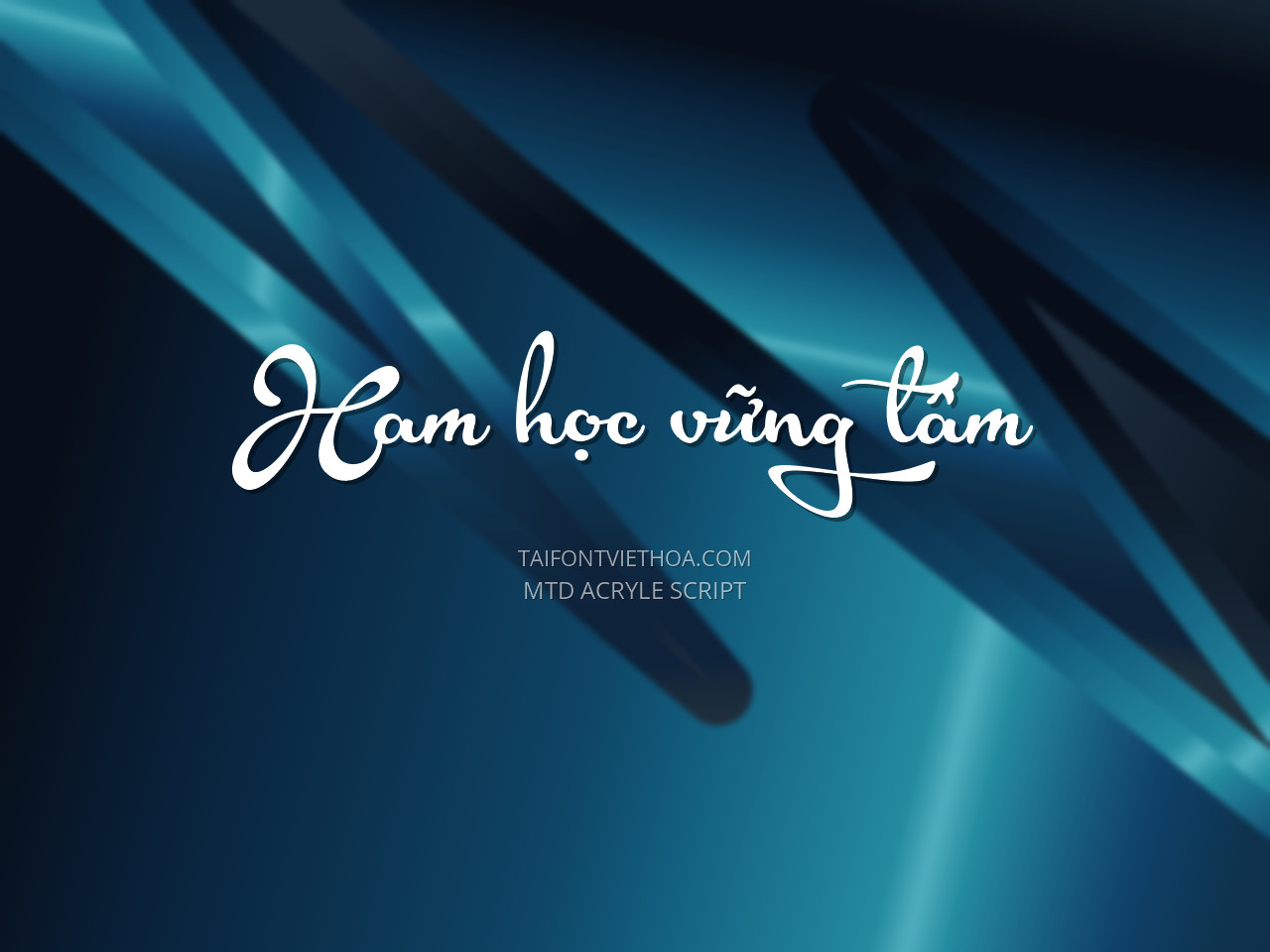
Font việt hóa MTD Acryle Script
Tác giả Font: Måns Grebäck
Giới thiệu về font Acryle Script – Vẻ đẹp viết tay tự nhiên và thanh lịch đầy nghệ thuật
Acryle Script là một kiểu chữ viết tay mang hơi hướng calligraphy hiện đại, được thiết kế với nét bút mềm mại, bay bổng và giàu biểu cảm. Font mô phỏng nét mực của bút lông hoặc cọ mềm, tạo cảm giác như được viết trực tiếp bằng tay một cách tỉ mỉ và duyên dáng. Sự kết hợp giữa tính nghệ thuật và cảm xúc khiến Acryle Script trở thành một lựa chọn tuyệt vời cho những thiết kế cần truyền tải thông điệp cá nhân, tình cảm hoặc sự sang trọng nhẹ nhàng.
Phiên bản Việt hóa do Mộc Hạthực hiện đã bổ sung đầy đủ bộ dấu tiếng Việt mà vẫn giữ nguyên được tinh thần thư pháp bay bổng của bản gốc. Taifontviethoa.comđã chọn lọc và chia sẻ font Acryle Script như một công cụ lý tưởng để sáng tạo trong các thiết kế liên quan đến thiệp mời, bao bì cao cấp, thương hiệu mang tính cá nhân hoặc cảm xúc sâu sắc.
Đặc điểm thiết kế uyển chuyển và ứng dụng nổi bật của font Acryle Script
Acryle Script nổi bật với các nét cong liền mạch, độ nghiêng chữ nhẹ, kết hợp ligatures mượt mà giữa các ký tự giúp dòng chữ trở nên linh hoạt và duyên dáng. Nét chữ có độ dày vừa phải, tránh cảm giác nặng nề, đồng thời tăng tính thẩm mỹ khi sử dụng ở kích thước lớn như tiêu đề, logo hay trích dẫn. Các ký tự thay thế (alternates) đi kèm giúp người dùng tùy biến sáng tạo hơn trong thiết kế.
Font đặc biệt phù hợp cho các ứng dụng như: thiệp cưới, logo thương hiệu mỹ phẩm, tiêu đề blog, trích dẫn nghệ thuật, thiết kế bao bì thủ công, hoặc nội dung mạng xã hội thiên về cảm xúc. Ngành nghề phù hợp: cưới hỏi, làm đẹp, thời trang, sản phẩm thủ công mỹ nghệ, thiết kế nội dung sáng tạo, lifestyle và các thương hiệu hướng tới sự mềm mại, lãng mạn và đầy nữ tính.